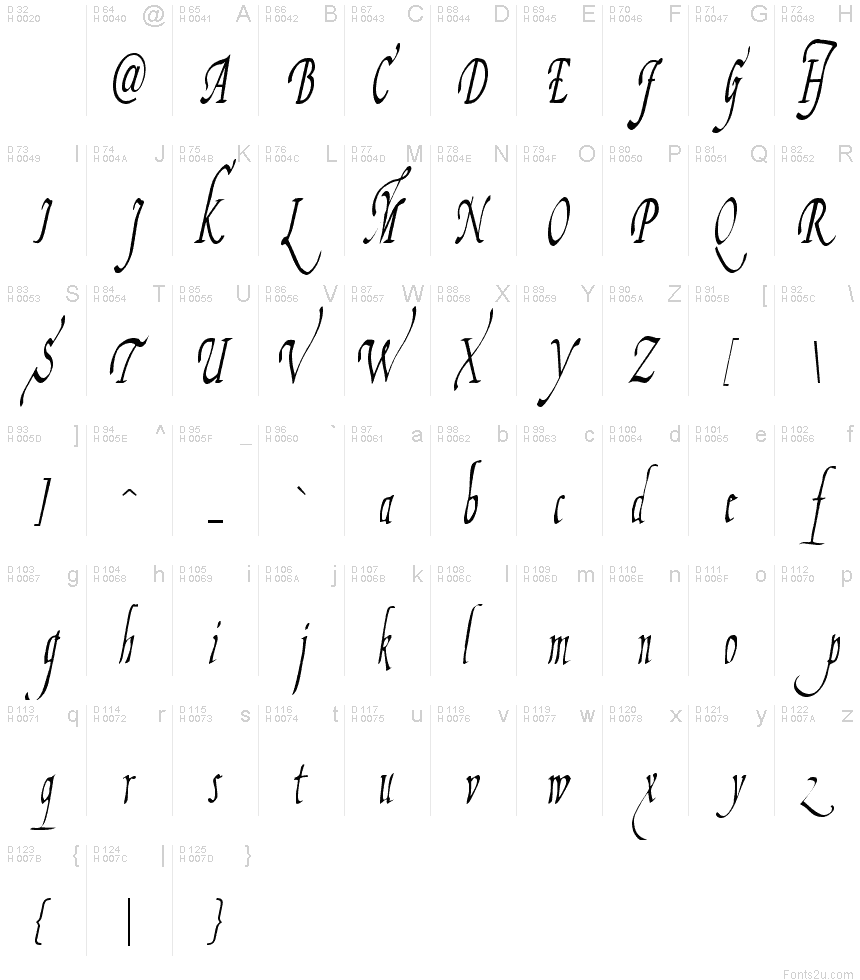
Fiorenza II autorstwa Davida F. Nalle to bezpłatny krój kaligraficzny o mrocznym, atramentowym charakterze. Jego wysokie, dynamicznie wygięte litery wyglądają, jakby zostały uchwycone w ruchu, łącząc ostre, rzeźbione pociągnięcia z krawędziami przypominającymi ślady pędzla, które sprawiają wrażenie niemal ręcznie wycinanych. Efektem jest nastrojowy skrypt, plasujący się gdzieś pomiędzy gotycką dramaturgią a włoską elegancją, o wąskim rytmie, który prowadzi wzrok wzdłuż słowa.
Ten bezpłatny font świetnie sprawdza się na etykietach win, okładkach książek, tytułach w stylu fantasy lub historycznych, logotypach butików, plakatach teatralnych i ozdobnych kartach menu. Zastosowanie Fiorenza II w większych rozmiarach pozwala w pełni wyeksponować jej surowe, teksturowe detale, podczas gdy połączenie jej z prostym szeryfowym lub czystym bezszeryfowym krojem w tekście głównym zapewnia czytelność i pozwala kaligrafii grać pierwsze skrzypce.